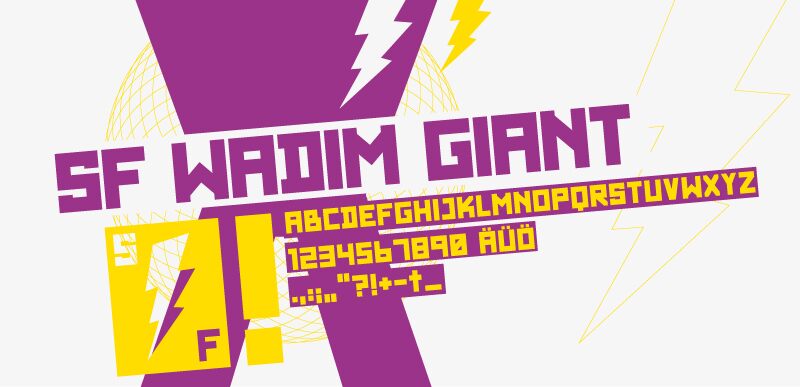
SF Wadim Giant Outline di Jens Nink è un font display techno con contorno gratuito, realizzato con maiuscole rigide e squadrate. La struttura lineare aperta, lo spessore del tratto uniforme, i netti angoli retti e i occasionali tagli diagonali conferiscono alle lettere l'aspetto di piste di circuiti o di segnaletica tecnica simile a un labirinto, con un tocco decisamente elettronico.
Si muove in modo convincente tra i titoli di interfacce di gioco e i poster di eventi nei club, poiché le sue forme vuote e modulari ricordano sia la grafica a schermo sia la segnaletica realizzata. Le stesse forme ingegnerizzate si adattano anche al packaging di musica elettronica, al merchandising arcade e all'editoria di fantascienza, dove il lettering può diventare parte di una rete o di un'illustrazione di circuiti più ampia.